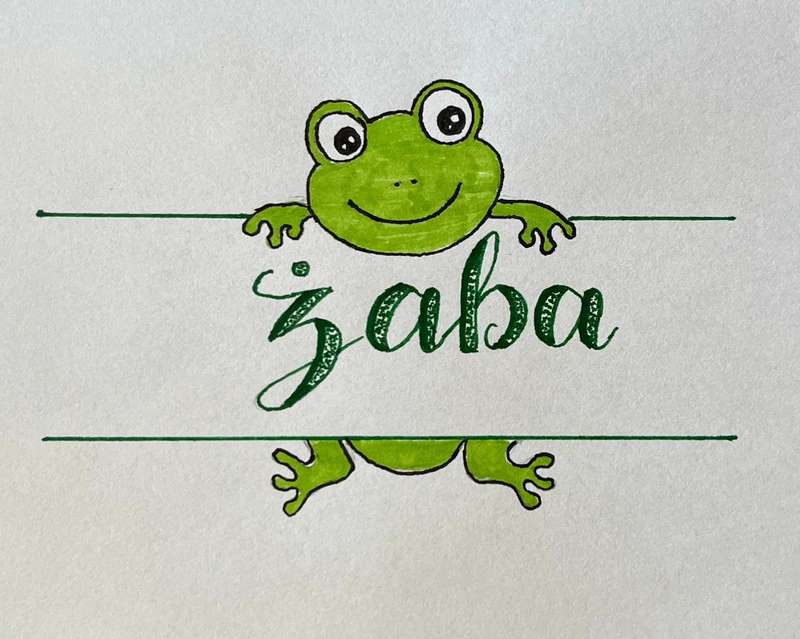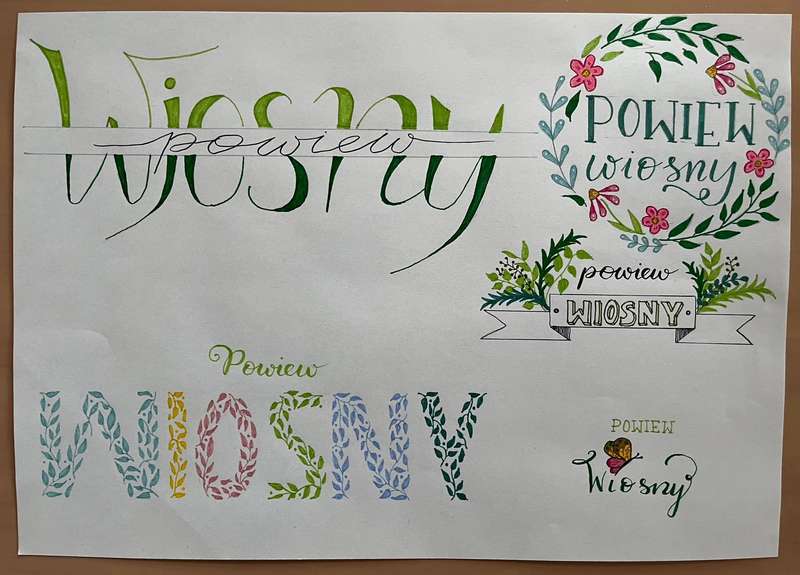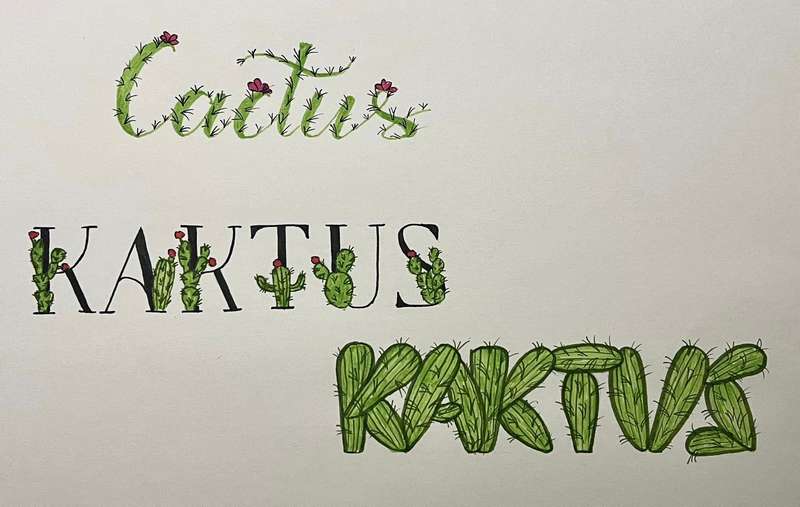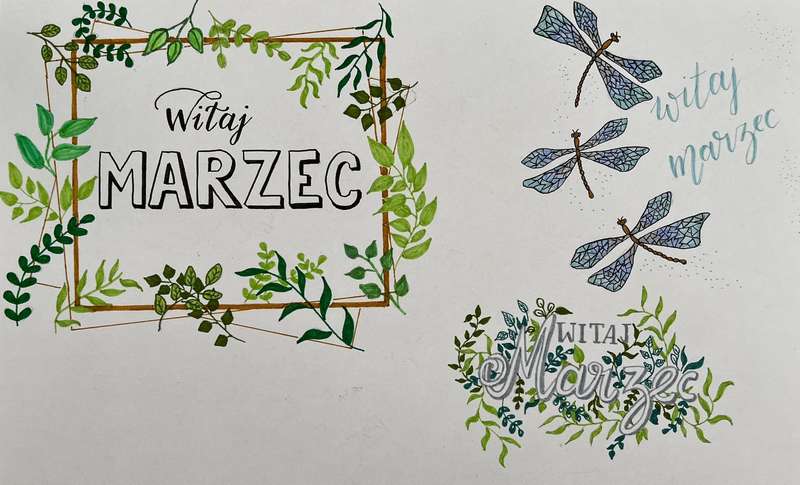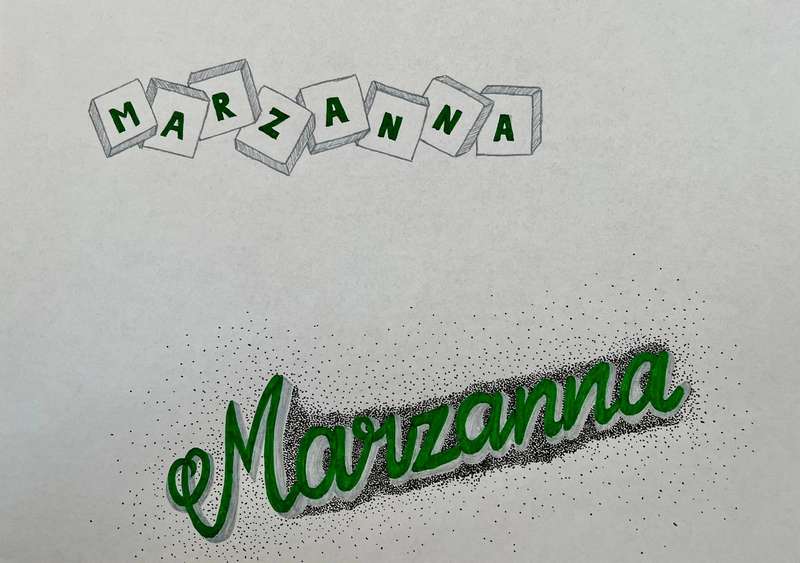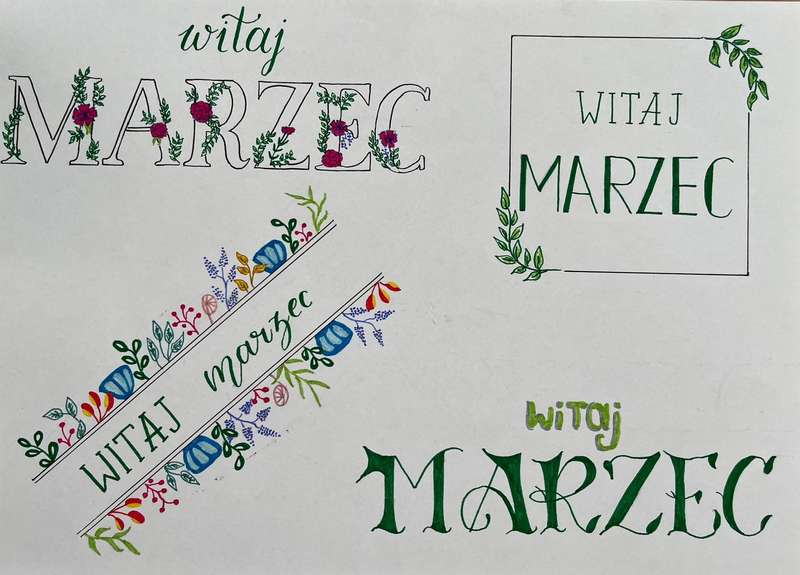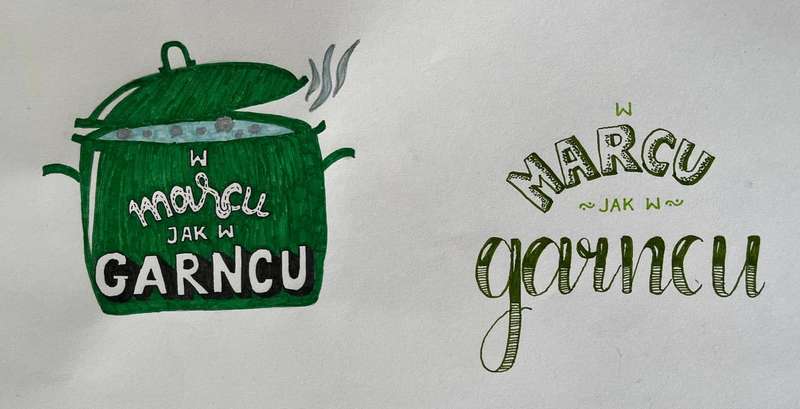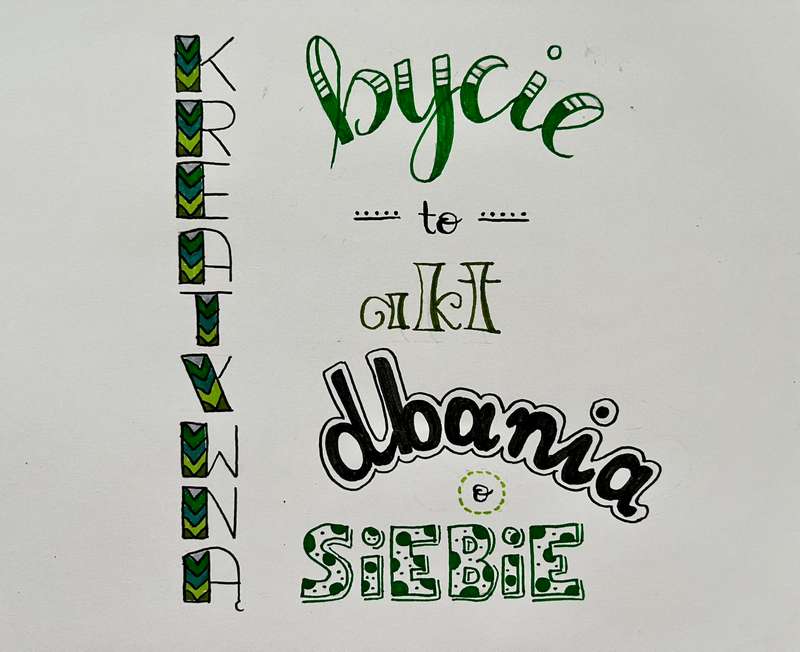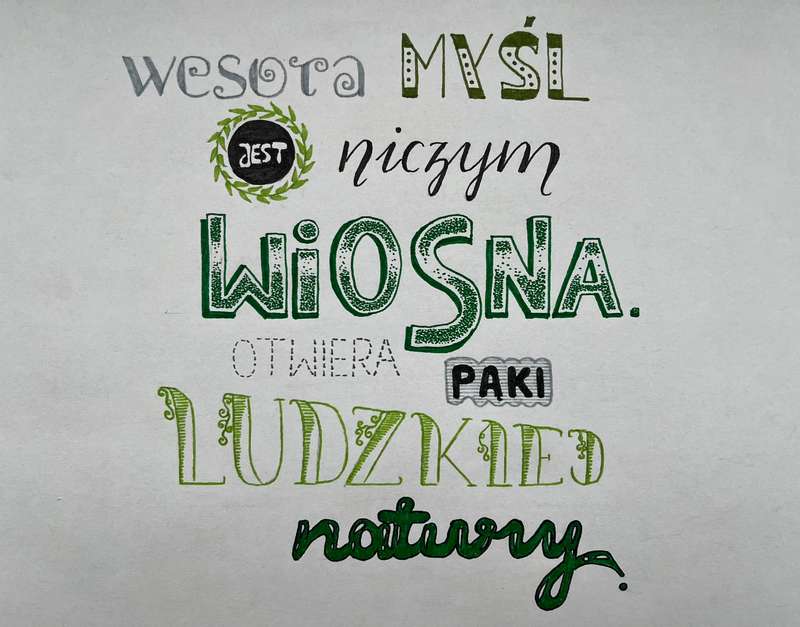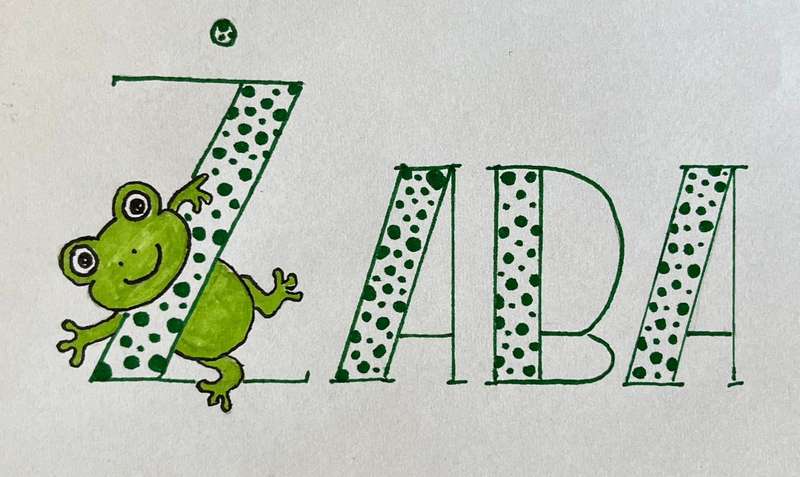
Co daje nam Hand lettering? Okiem Marceliny [wywiad]
Co daje nam Hand lettering
Zawsze powtarzam:
„Lettering to moja joga dla umysłu”, dlatego byłam strasznie ciekawa, co odczuwają inni praktykując hand lettering. Właśnie dobiegło końca nasze wyzwanie „Zielony marzec„. Postanowiłam zapytać -Marcelinę, zwyciężczynię wyzwania, jakie ma odczucia po wyzwaniu, czego się nauczyła. Co daje jej po prostu udział w wyzwaniu. Marcelina wykonała wszystkie hasła (niektóre nawet kilkakrotnie w różnych wariantach). Zapraszam na wywiad z Marceliną.
Marcelina, kiedy zaczęła się Twoja przygoda z hand letteringiem? Pamiętasz, co Cię w nim zafascynowało?
Pierwszy moment, który mnie zainspirował i zmobilizował, miał miejsce pod koniec 2022 roku, czyli dosyć dawno. Przeglądając social media, trafiłam na bullet journal. Zaczęłam zgłębiać temat, oglądać różne projekty, czytać o planerach. Bardzo mi się spodobał taki sposób planowania i uporządkowania wszystkich swoich zadań, ważnych spraw, wydarzeń czy celów. Na tamten moment uznałam, że nie jestem gotowa na prowadzenie swojego bujo, bo brakuje mi podstaw. Postanowiłam to nadrobić i brnąc przez meandry internetu trafiłam na pierwsze wzmianki o hand letteringu, o którym do tej pory gdzieś słyszałam, ale mylnie wiązałam to z kaligrafią. Zaczęłam zapoznawać się z tematem, znalazłam szablony do ćwiczeńi kupiłam swoje pierwsze brush peny. Później, jak to często bywa, rutyna, codzienne obowiązku, a w efekcie brak czasu i chęci na kreatywność. Ta, nazwijmy ją, artystyczną stagnacją, trwała ponad rok. Coś drgnęło, kiedy na początku tego roku trafiłam do Ciebie na kurs hand letteringu. Te cykliczne spotkania udowodniły, że mogę się zorganizować i znaleźć chwilę dla siebie. Od tej pory poszło już z górki i dbam o to, by ćwiczyć regularnie. Co mnie fascynuje? Hand lettering to piękny sposób wyrażania siebie, swoich myśli. Jest to także sposób na odprężenie, rozładowanie emocji nagromadzonych w ciągu całego dnia. A przede wszystkim można stworzyć coś niepowtarzalnego, podarować komuś własnoręcznie przygotowaną pracę i spowodować, by obdarowana osoba poczuła się wyjątkowo.
Hand lettering
Co daje nam Hand lettering
Każda z Twoich prac jest coraz bardziej precyzyjna i przyciąga oko ilością detali. Wiele razy powtarzam kursantkom – hand lettering to nie sprint, lecz maraton. Po jakim czasie zauważyłaś swoje postępy?
Cieszę się, że widać progres, chociaż jeszcze dużo pracy przede mną. Myślę, że po około miesiącu zauważyłam, że łatwiej prowadzi mi się brush peny i nie robię tego tak  nerwowo jak wcześniej. Na początku pisałam właściwie codziennie. Po trochu, ale codziennie. Teraz staram się wygospodarować czas co najmniej 3 razy w tygodniu i jest to minimum, które poświęcam na ćwiczenia. Dodatkowo bardzo lubię podpatrywać w sieci projekty hand letteringowe, różne kompozycje. To jest kopalnia inspiracji. Na to też poświęcam trochę czasu. Cieszę się, że żyjemy w takich czas, że rozwój technologiczny pozwala dzielić się swoimi pomysłami i czerpać z pomysłów innych.
wyzwanie hand letteringowe
Co daje nam Hand lettering
Co daje Ci hand lettering? Jak się czujesz praktykując hand lettering, pisząc ciekawe hasła, sentencje lub ćwicząc pojedyncze wyrazy? Masz może swoją ulubioną technikę?
Czas, który spędzam z hand letteringiem to mój czas, przeznaczony tylko dla mnie. Jest to dla mnie moment odpoczynku, relaksu, rozładowania emocji, wyciszenia i skupienia. Pisanie mnie uspokaja. Kiedy zastanawiam się nad jakąś kompozycją, robię szkic, poprawiam go kilka razy, później znowu zmieniam, wyłączam się całkowicie i moje myśli krążą już tylko wokół pomysłu, jego wykonaniu i przeniesieniu na papier. Radość sprawia mi również przygotowanie spersonalizowanych drobiazgów dla znajomych, karteczek z życzeniami miłego dnia dla dzieci do śniadaniówek. To takie akcenty, które powodują, że dzień od razu staje się piękniejszy. Jeśli chodzi o technikę, to bardzo podoba mi się bounce lettering i ta figlarność liter, ale ta przyjemność dopiero przede mną. Myślę, że muszę jeszcze sporo poćwiczyć, by zacząć zabawę z tańczącymi literami, bo one tylko sprawiają wrażenie takich hmmm… niedbałych. Trzeba poczuć i znaleźć ten ich rytm, który spowoduje, że napis stanie się niezwykle atrakcyjny.
wiosna lettering
zielony marzec lettering
Co dał Ci udział w wyzwaniu letteringowym „Zielony marzec”?
Udział w wyzwaniu przede wszystkim pomógł mi w utrzymaniu regularności w ćwiczeniu pisania. Spowodował, że moje myśli krążyły wokół kreatywnych tematów. Mogę powiedzieć, że hand lettering towarzyszył mi całe dnie, a marzec zdecydowanie upłynął pod jego znakiem. Wyzwanie było świetną odskocznią, motywacją, mobilizacją oraz zabawą. Przygotowywałam swoje prace, podziwiałam projekty innych uczestników wyzwania. Czas spędzony nad pisaniem haseł z „zielonego marca” był niezwykle kreatywny, a przy okazji ćwiczył rękę, odprężał i stwarzał przestrzeń dla wyobraźni. Gdzieś przeczytałam, że jednym ze sposobów na pobudzenie kreatywności jest właśnie ręczne pisanie. Całkowicie się z tym stwierdzeniem zgadzam i podpisuję się pod nim obiema rękami.
wyzwanie letteringowe
zaba lettering
Jakie wskazówki możesz dać osobom początkującym? Jak zacząć naukę?
Początkującym, w pierwszej kolejności, proponuję „przekopać” internet w poszukiwaniu podstawowych informacji i porad, a także skorzystać z doświadczeń osób, które są już na wyższych poziomach wtajemniczenia. Ważne jest, by się nie zniechęcać i nie omijać tych pierwszych ćwiczeń (szlaczków). One może w pewnym momencie stają się nudne, ale są niezwykle potrzebne i później się to docenia. Niektóre litery są łatwiejsze w pisaniu, inne, wydawałoby się, niepozorne, sprawiają wiele problemów, a ich pisanie może powodować pewnego rodzaju irytację. Należy podejść do tematu metodycznie, uzbroić się w cierpliwość i ćwiczyć. To naprawdę przynosi efekty.
Co zrobić, aby się nie zrazić, jeśli nie widzimy natychmiastowych postępów?
Bardzo ważne jest też, by pamiętać o rozgrzaniu ręki przed pisaniem wyrazów. Tak przygotowana ręka lepiej i pewnie prowadzi brush pen. I na koniec… jestem strasznym gadżeciarzem, jeśli chodzi o artykuły papiernicze i piśmiennicze. Zapewne już dawno bym zbankrutowała, gdybym nie przeczytała m.in. na Twoim blogu, żeby nie wykupywać całego sklepu z asortymentu do hand letteringu. I to dobry ruch. Trzeba się powstrzymać i podejść do tematu na chłodno, a na początek kupić jedynie podstawowe wyposażenie korzystając z porad i recenzji, które można znaleźć w sieci, a całą uwagę zamiast na tych wszystkich pięknych i kolorowych rzeczach, skierować na ćwiczenia. Wszystkim początkującym życzę cierpliwości i frajdy z pisania, bo ostatecznie chodzi o to, by znaleźć swój sposób na odprężenie i zregenerowanie nerwów, organizmu po ciężkim dniu czy tygodniu. Bawcie się hand letteringiem, bo to równie ważne jak ćwiczenia. Radość i przyjemność z pisania będzie widoczna w każdym projekcie, nawet jak nie będzie on idealny technicznie.